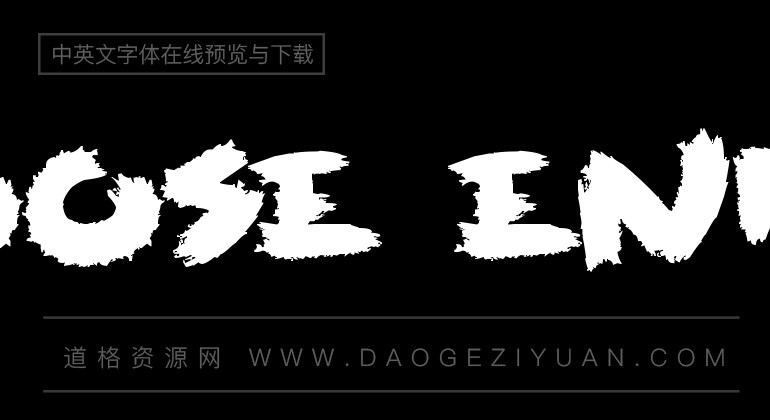
Loose Ends
Loose Ends 是一款抽象风格的字体,由英国设计师Tom Chalky设计,它采用抽象的线条和自由的笔触,拥有极具个性的外观,可以满足多种不同的设计需求,包括商业广告、海报、印刷品等。Loose Ends具备良好的可读性,可以清晰地展现出文字的内容,同时也具备强大的表现力,可以使设计更加生动有趣。
Loose Ends是一款非常不错的手写艺术字体,具有很好的视觉感,适合于文化类的宣传设计、商业类品牌的广告和产品包装设计以及个性化文字排版等较多场景。